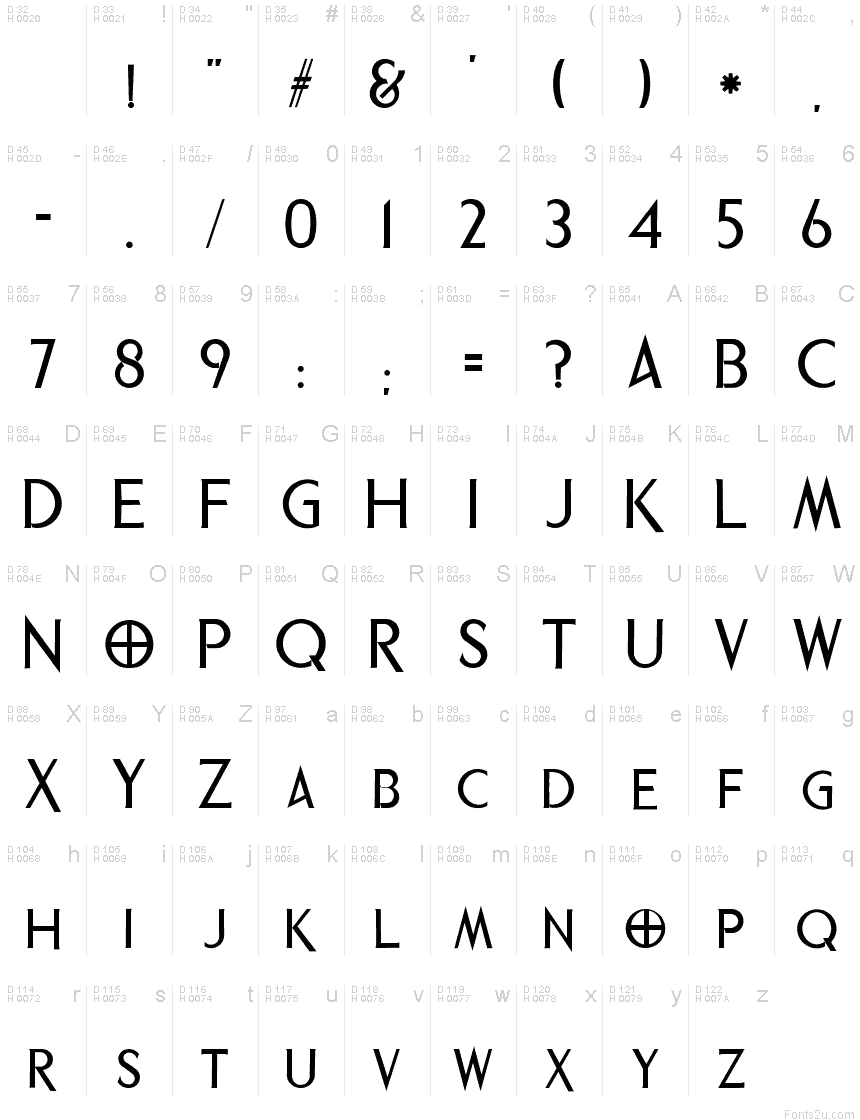
Phrixus autorstwa Waltera Veleza to darmowy, bezszeryfowy krój w stylu Art Déco, oparty na wysokich wielkich literach, zdecydowanych kreskach i czystych, geometrycznych cięciach. Litery wydają się minimalistyczne, a zarazem teatralne, z szerokimi pionami, kwadratowymi łączeniami i kilkoma ostrymi przekątnymi, które nadają fontowi rytm znany z dawnych plakatów, daleki od współczesnej neutralności.
Świetnie odnajduje się w tytułach filmów w stylu vintage, identyfikacji wizualnej koktajlbarów, okładkach książek, plakatach imprezowych czy monogramach, gdzie wydłużone kapitałki dodają krótkim tekstom wyrazistości. Jako darmowy font, Phrixus sprawdza się najlepiej, gdy dasz wybrzmieć światłu między znakami i samym sylwetkom liter – szczególnie w tytułach czy okładkach, które mają przywoływać klimat lat 20. bez zbędnych ozdobników.